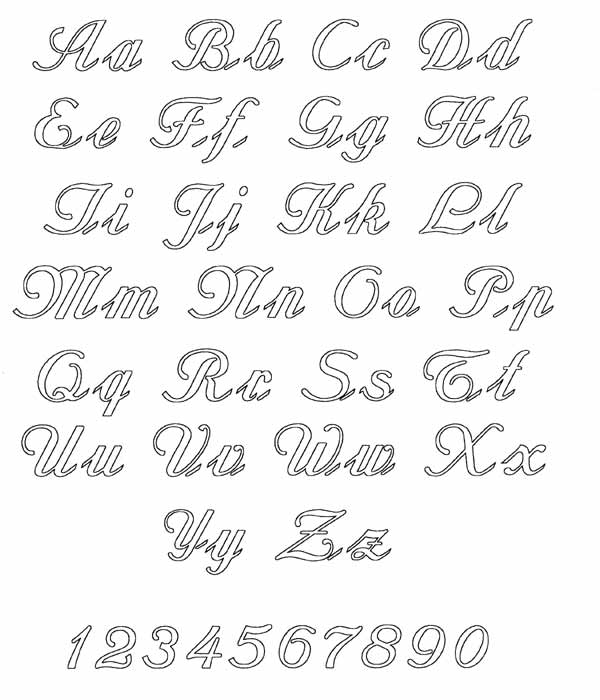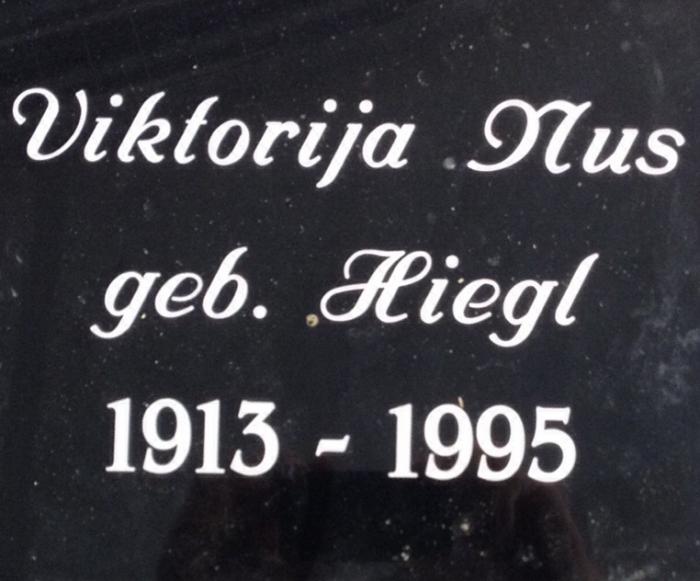
Suche Schrift für eine Ergänzung einer Grabplatte
die Schrift, die ich suche, ist auf einer Aluplatte letztes Jahr graviert worden. Leider ist der damalige Auftraggeber verstorben und so suche ich nach dieser Schriftart. Hat jemand einen Tipp?
ich denke das wird sie sein, auch wenn die Zahlen nicht übereinstimmen. Ich rufe mal den Kollegen an … Wir arbeiten noch traditionell und entwerfen/zeichnen die Schriften per Hand bzw. haben ein paar handgezeichnete Schriften digitalisiert.
In diesem Zusammenhang muss ich einfach bemerken, dass das typografische Schaffen und die Bedeutung für unsere heutige Schrift der Steinmetzzunft viel zu wenig erwählt wird. Ich habe irgendwo gelesen, dass die alten Meister der Schriftgestaltung, wie Aldus Manutius, Francesco Griffo oder Claude Garamond ihre eleganten und bis heute viel genutzten Antiquaschriften nach Grabstein-Inschriften gestaltet haben, während die Gotischen, Schwabacher und Frakturschriften die Handschriften der Klöster nachzuahmen suchten.
Die Namen der alten Meister des Stempelschneidens sind bis heute bekannt und stehen für hervorragende Schriften, und sind noch immer Vorbilder für Schriftgestalter überall auf der Welt, die Steinmetzte aber, von denen eigentlich die Formen stammen, kennt jedoch niemand.
Ich wär jedenfalls sehr an solchen Vorlagen interessiert, die noch nicht digitalisiert sind, aber auch am Namen dessen, der sie gezeichnet hat.
ich denke das wird sie sein, auch wenn die Zahlen nicht übereinstimmen.
Die Zahlen aus deinem Beispiel sind auch nicht aus dieser Schrift gesetzt, sondern aus einer Benguiat(-ähnlichen).
Wie ich so etwas finde? Einfach "Grabstein Schriftart" bei der Google-Bildersuche eingeben und 2 Minuten Zeit zum Durchblättern investieren ;-)
Als ich den Schrift gesucht habe dachte ich nicht an eine Grabmal-Inschrift da der Kunde die gezeigte Aluplatte vor einem Jahr selber gebracht hat und wir sie nur montiert haben. Daher dachte ich es wäre eine typische Computer-Gravier-Schrift … Anbei mal ein digitalisierte Schrift die ich mit einer Schnurzugfeder gezeichnet habe.